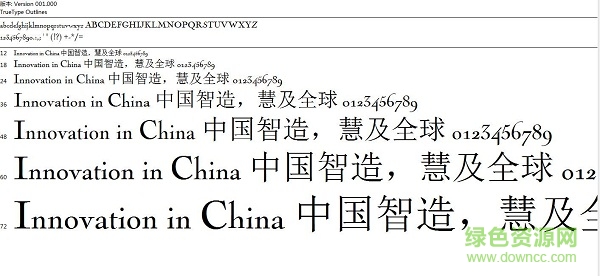
nicolas cochin字體是一款老式風格的襯線字體,豎線極長,筆鋒突出,襯線精致,粗細對比明顯,廣告商標、雜志海報等均可采用該字體,時尚感十足,歡迎大家免費下載!
老式字體往往能與亞現代(過渡)字體混合,這是因為亞現代字體在設計時融合了老式字體的風格,同時兼?zhèn)洮F代字體的簡單,這是字體既不相同,又能相互協(xié)調。同一份設計中的不同字體應有自己的大小和間距,以便相互之間的融合。